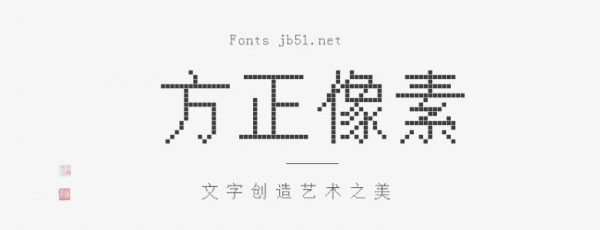
方正像素是一款用于電子屏幕的功能性字體。這款字體基于黑體和宋體的基本字形,每個字的像素顆粒由手工設(shè)定,在保證易識性和美觀性的同時滿足屏幕設(shè)備上的點(diǎn)陣數(shù)量。方正像素家族包含6款字體,其中數(shù)字代表最長邊的點(diǎn)陣數(shù),適用于LED屏和針式打印機(jī)等設(shè)備。此外,小字號的方正像素具有一定的易讀性,還可在傳統(tǒng)印刷媒介中用于機(jī)械和科技類的文本。